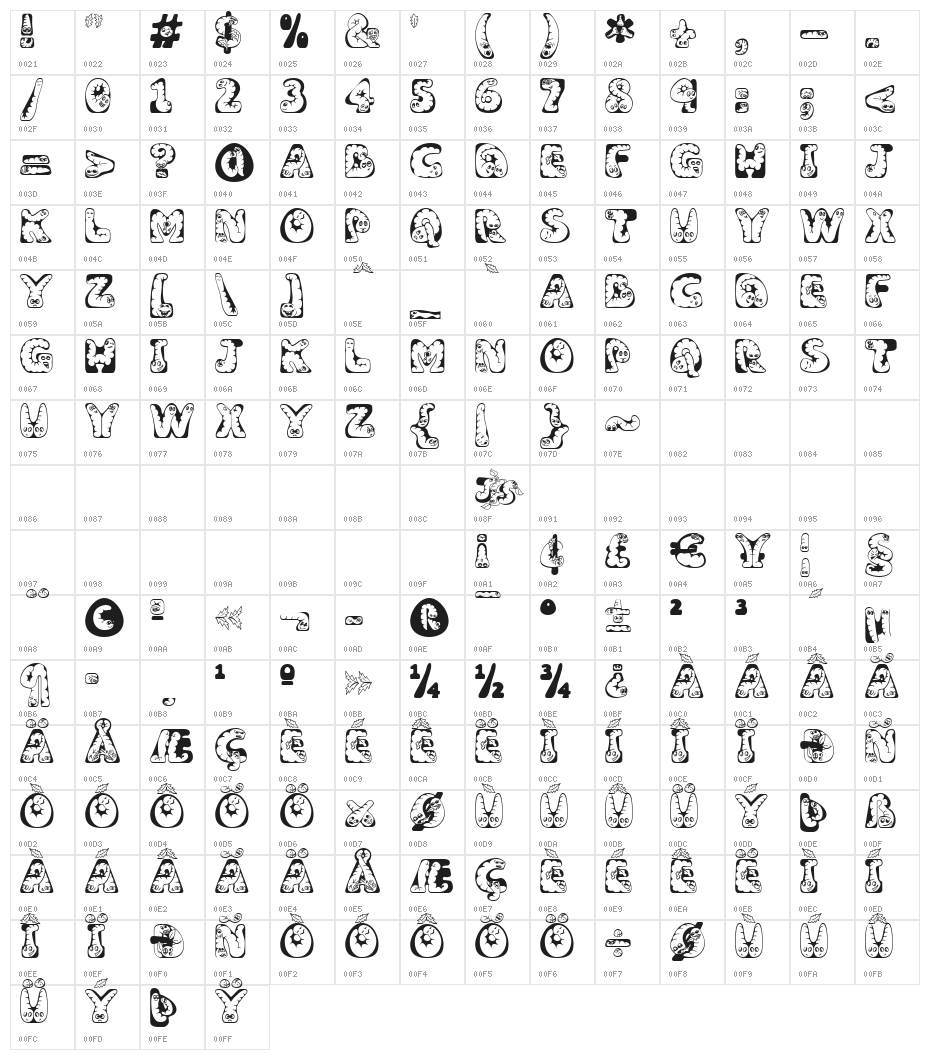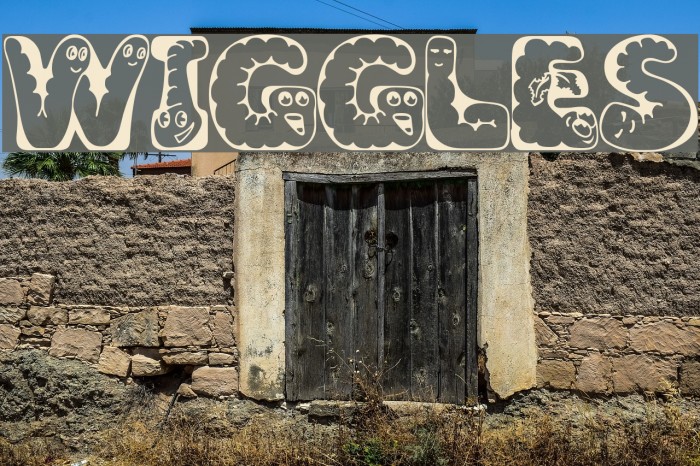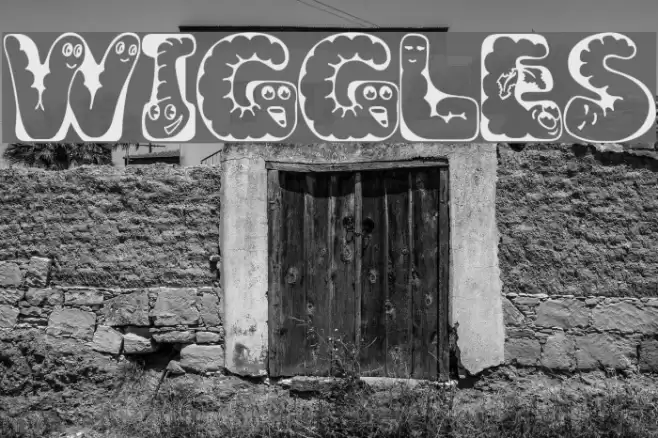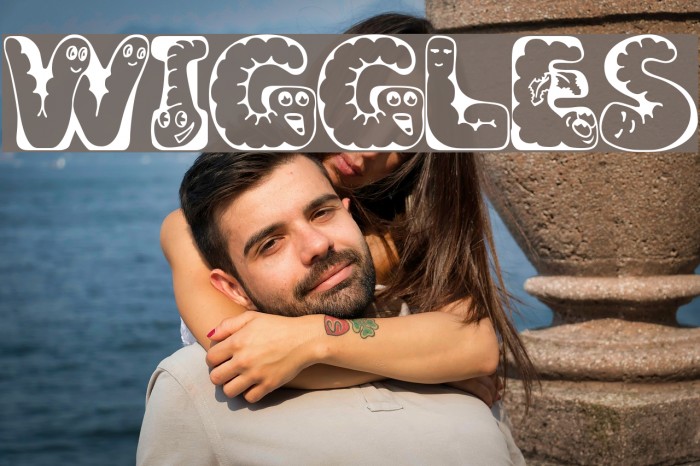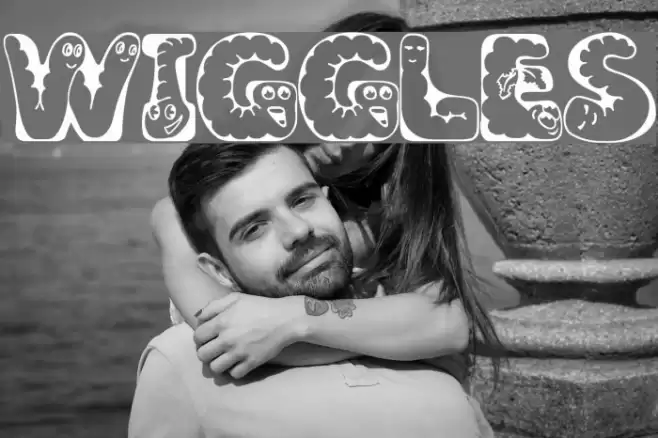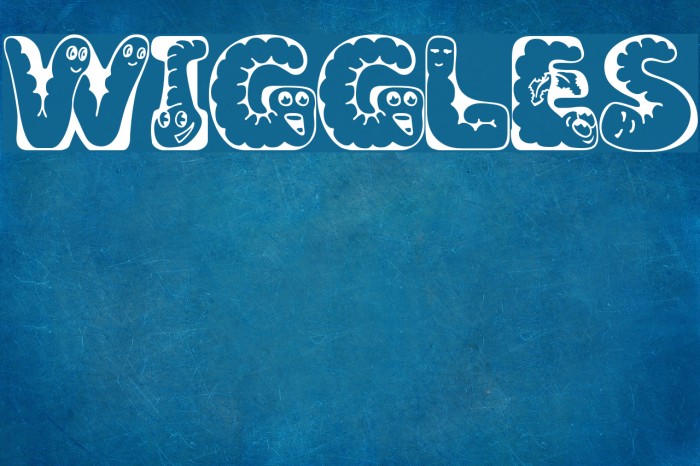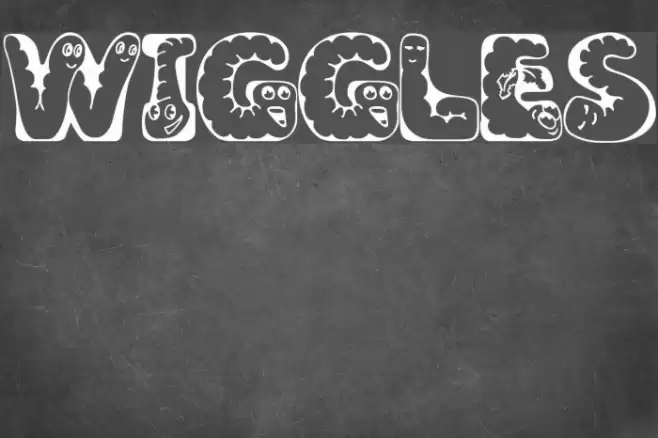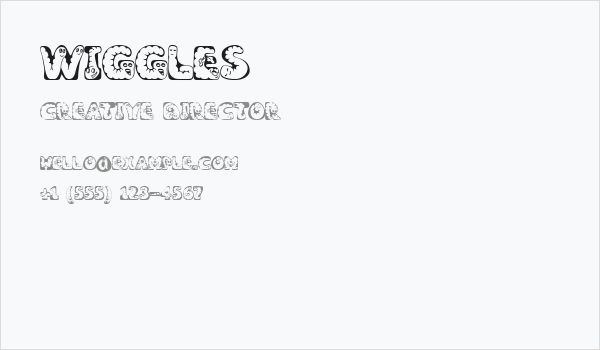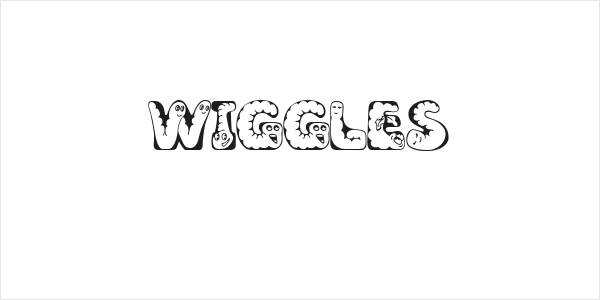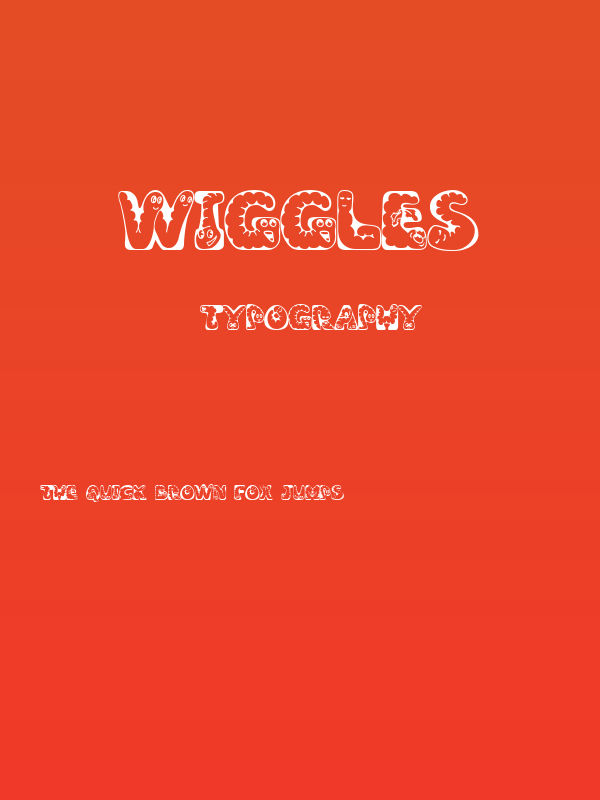
Wiggles Font
✎ Capitals
Fonts by Apostrophic Lab
| Nome | Wiggles |
| Categorie | Capitals |
| Stile generale | Playful, Whimsical, Cartoon-like |
| Progetti proposti | Children's books, playful branding, creative posters, party invitations. |
Wiggles
| Nome | Wiggles |
| Autore | Fonts by Apostrophic Lab |
| Categorie | Capitals |